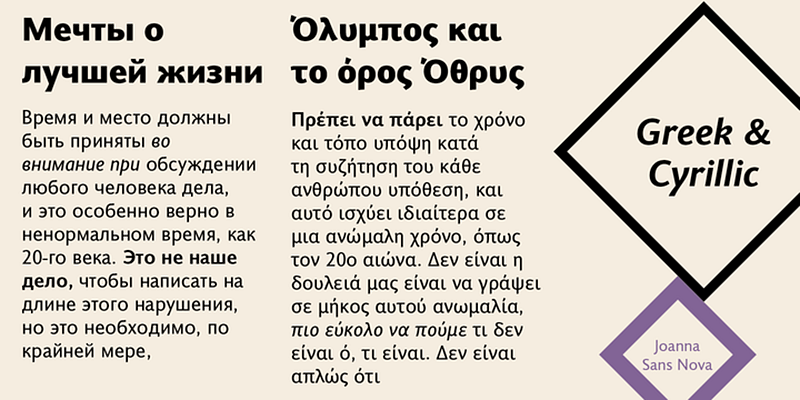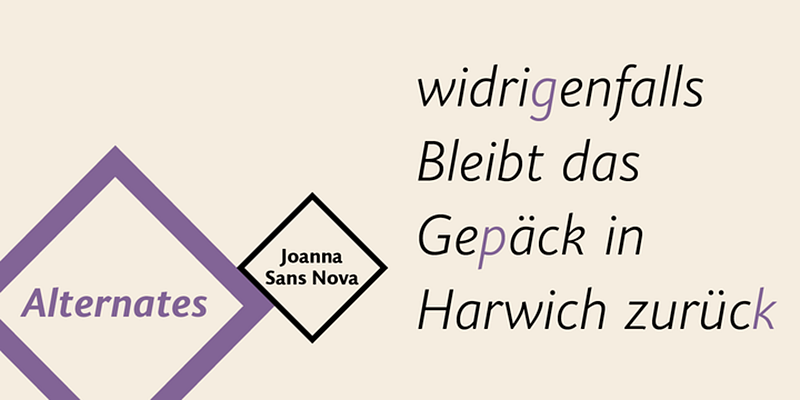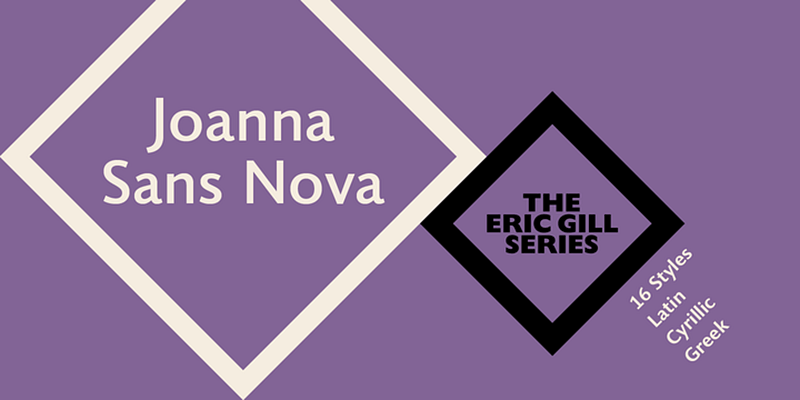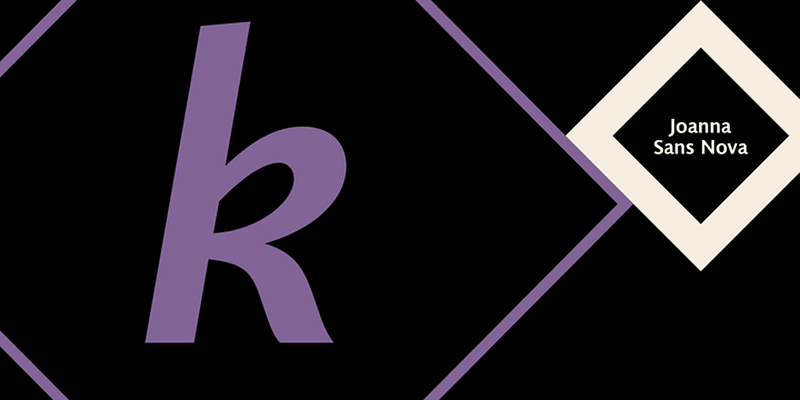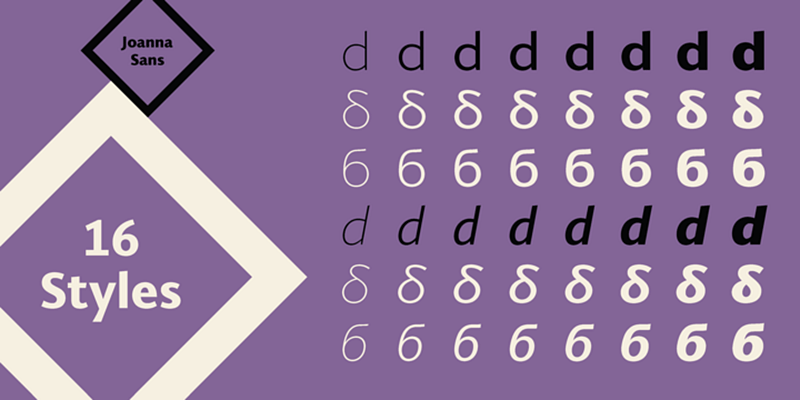
Joanna® Sans Nova ファミリーは、Eric Gill シリーズの中で唯一、もともと Gill 氏によってデザインされていない書体です。Monotype Studio のデザイナーである Terrance Weinzierl 氏が 3 年の歳月をかけて、デジタルアプリケーションをデザイン基準の最前線に据えて作成した Joanna Sans Nova は、Gill 氏のオリジナルの Joanna を主にベースとしたヒューマニスト体サンセリフです。デザインは、Thin から Black まで 16 種類のフォントで構成され、それぞれにイタリック体が付属しています。Joanna Sans Nova は、小さなデジタル画面でも高い可読性を確保するために、x ハイトが大きめになっています。Joanna Sans Nova は、ヒューマニストなプロポーションを持つため、長文の読み物でも驚くほど快適に使用できます。文字の線のウエイトの低コントラストも、様々な環境でのイメージングを向上させます。さらに、カリグラフィの滑らかなディテールにより、ローマン体とイタリック体のデザインが見出しやその他のディスプレイ用途で際立ちます。
Joanna Sans は、スモールキャップス、オールドスタイルの数字、プロポーショナル数字、合字、上付き数字と下付き数字、分数のサポートなど、洗練されたタイポグラフィを実現する豊富な OpenType 機能を特徴としています。フォントごとに 1,000 以上のグリフを収録し、ラテン文字、ギリシャ文字、キリル文字など 50 以上の言語をサポートしています。